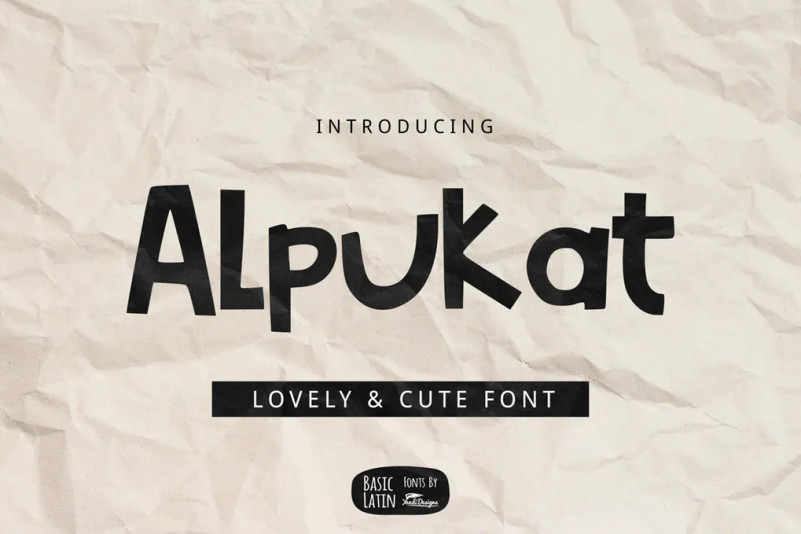
Alpukat Font
Alpukat Font est simple et mignon police multi-usage fait à la main, adapté pour de nombreux projets enfants livre, citations, Logo, titre, etc.